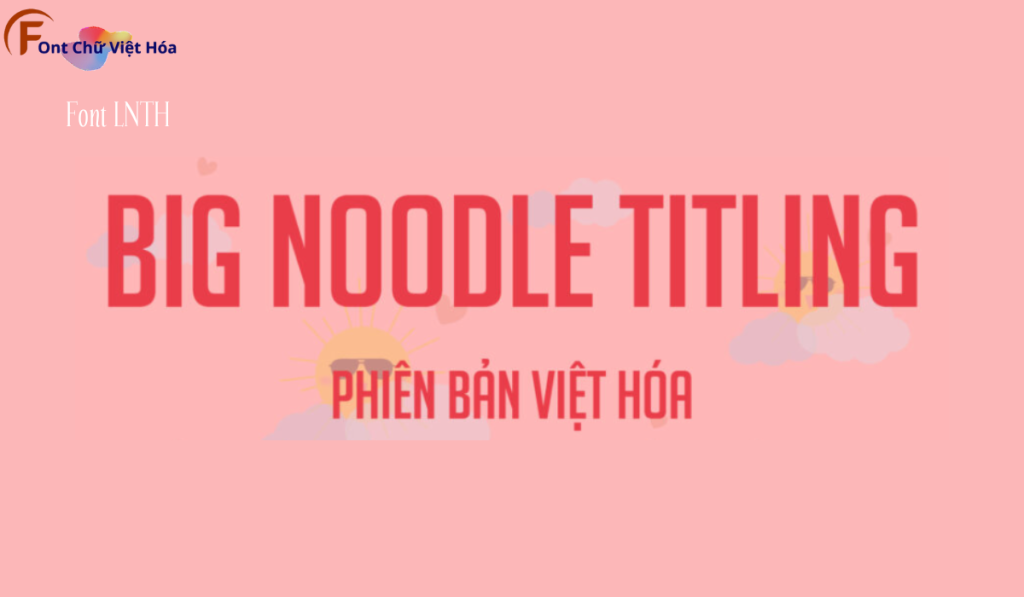
LNTH Bignoodle Titling Font Việt Hóa
LNTH Bignoodle Titling Font Việt Hóa là một font chữ mạnh mẽ, thuộc bộ LNTH, với thiết kế đậm và nổi bật. Phong cách của font này phù hợp với các dự án thiết kế cần sự mạnh mẽ và thu hút, như poster, tiêu đề, hoặc bảng hiệu quảng cáo. LNTH Bignoodle Titling Font Việt Hóa mang đến sự nổi bật và dễ nhận diện, ứng dụng trong các lĩnh vực sáng tạo. Đặc điểm hình dạng của font bao gồm các đường nét dày và chắc chắn, giúp tăng tính thẩm mỹ và sự chú ý. Việc Việt hóa font giúp người dùng dễ dàng sử dụng trong các thiết kế tiếng Việt, mang lại sự tiện lợi và linh hoạt.